font-smooth
非标准: 该特性尚未标准化。我们不建议在生产环境中使用非标准特性,因为它们在浏览器中的支持有限,且可能发生变化或被移除。不过,在没有标准选项的特定情况下,它们可以作为合适的替代方案。
font-smooth CSS 属性控制字体渲染时应用的抗锯齿效果。
备注:Webkit 实现了名为 -webkit-font-smoothing 的相似属性。该属性仅适用于 macOS。
- auto——由浏览器决定(如果可用,则使用亚像素抗锯齿;这是默认值)。
- none——关闭字体平滑;显示带有锯齿边缘的文本。
- antialiased——在像素(而不是亚像素)级别平滑字体。对于深色背景上的浅色文本,从亚像素渲染切换为抗锯齿渲染可以使其看起来更清晰。
- subpixel-antialiased——在大多数非视网膜显示器上,这将会提供最清晰的文本。
备注:Firefox 实现了名为 -moz-osx-font-smoothing 的相似属性。该属性仅适用于 macOS。
- auto——允许浏览器选择字体平滑的优化方式,通常为- grayscale。
- grayscale——用灰度抗锯齿(而不是亚像素)渲染文本。对于深色背景上的浅色文本,从亚像素渲染切换为抗锯齿渲染可以使其看起来更清晰。
font-smooth = auto | never | always | <absolute-size> | <length>
>基础使用示例
以下示例展示了在 macOS 上打开字体平滑的 Safari/Chromium 和 Firefox 的等效结果。对于这两类情况,平滑的字体应该看起来更细一些。
对于那些没有使用 macOS 系统的用户,这里有一张截图(后面会有实时版本):
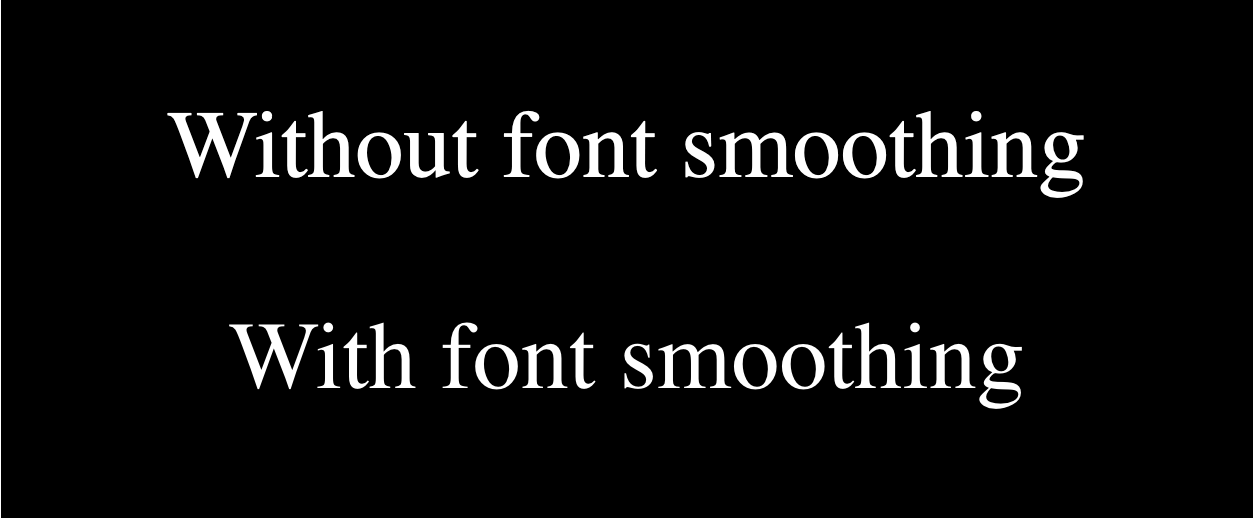
结果
规范
不属于任何规范。